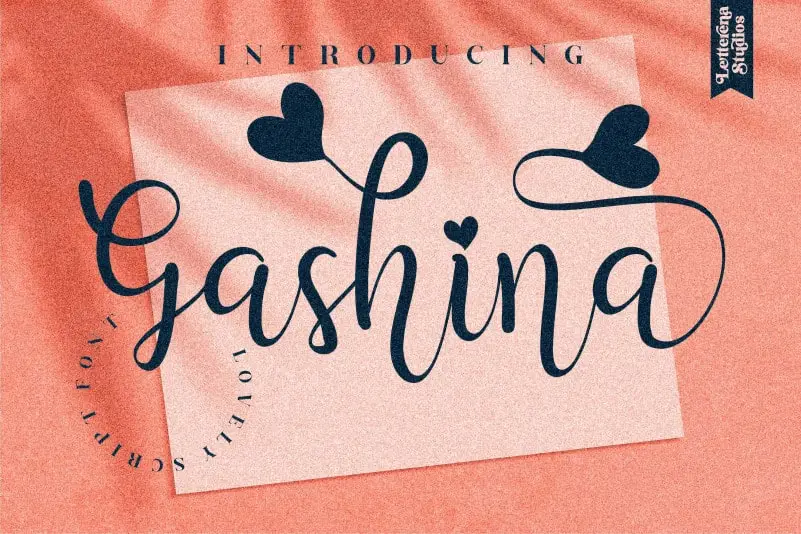
Gashina Handwritten Font – Download Grátis
A Gashina Handwritten Font é uma elegante escolha para aqueles que buscam adicionar um toque romântico aos seus projetos digitais. Ela traz duas tipografias diferentes e swashes de coração para criar um estilo de escrita chamada calligrafia. Esta fonte atraente é perfeitamente adequada para uma variedade de projetos, desde logomarcas e criação de marca até embalagens de produtos, mug decorativos, citações, cartazes, sacolas de shopping, camisetas, capas de livros, cartões de nome, convites, cartões de agradecimento, selos, fotografias e eventos especiais. A Gashina Handwritten Font é a solução perfeita para todos os seus projetos que precisam daquela pitada única de uma escrita delicada e charmosa.